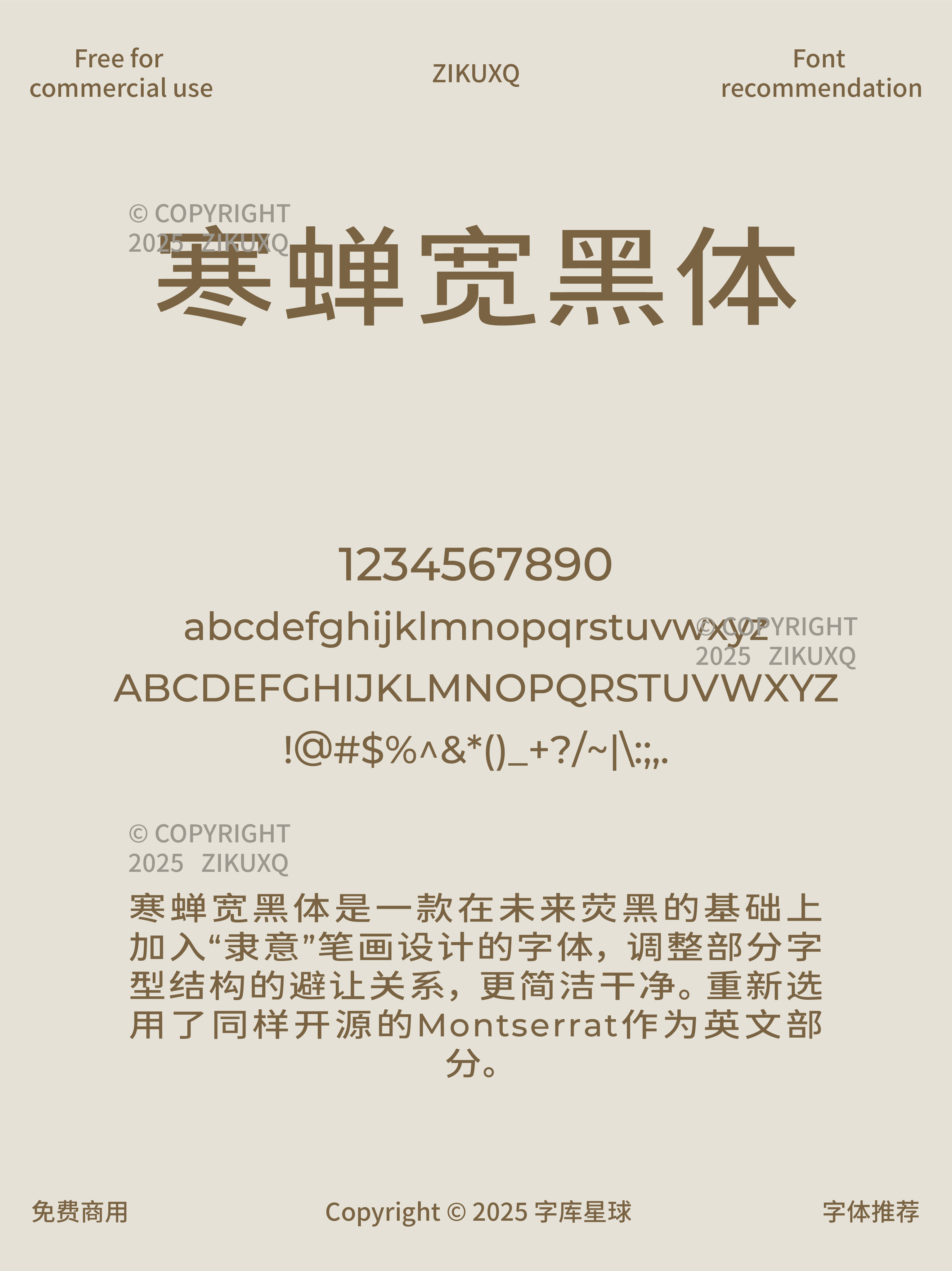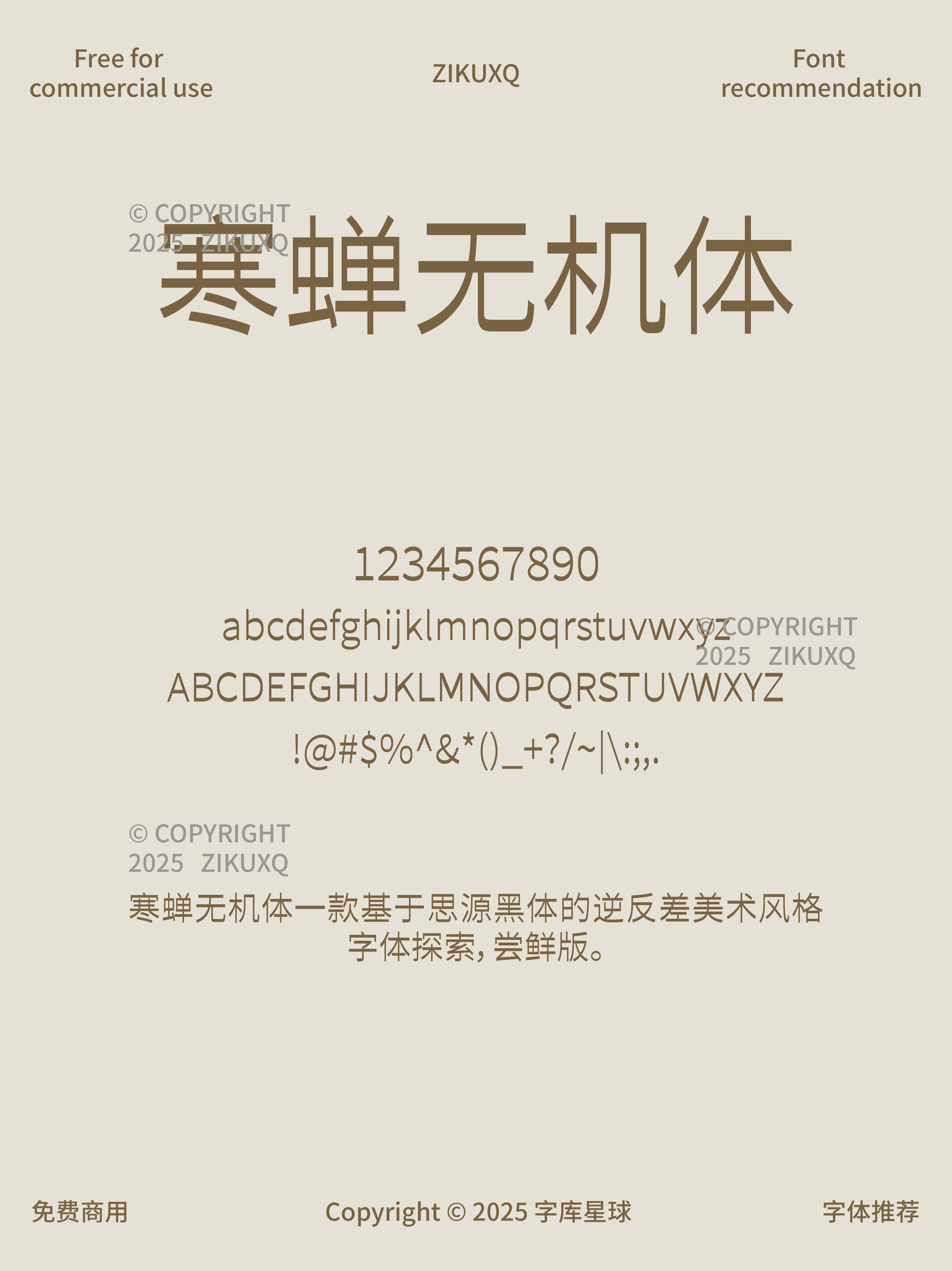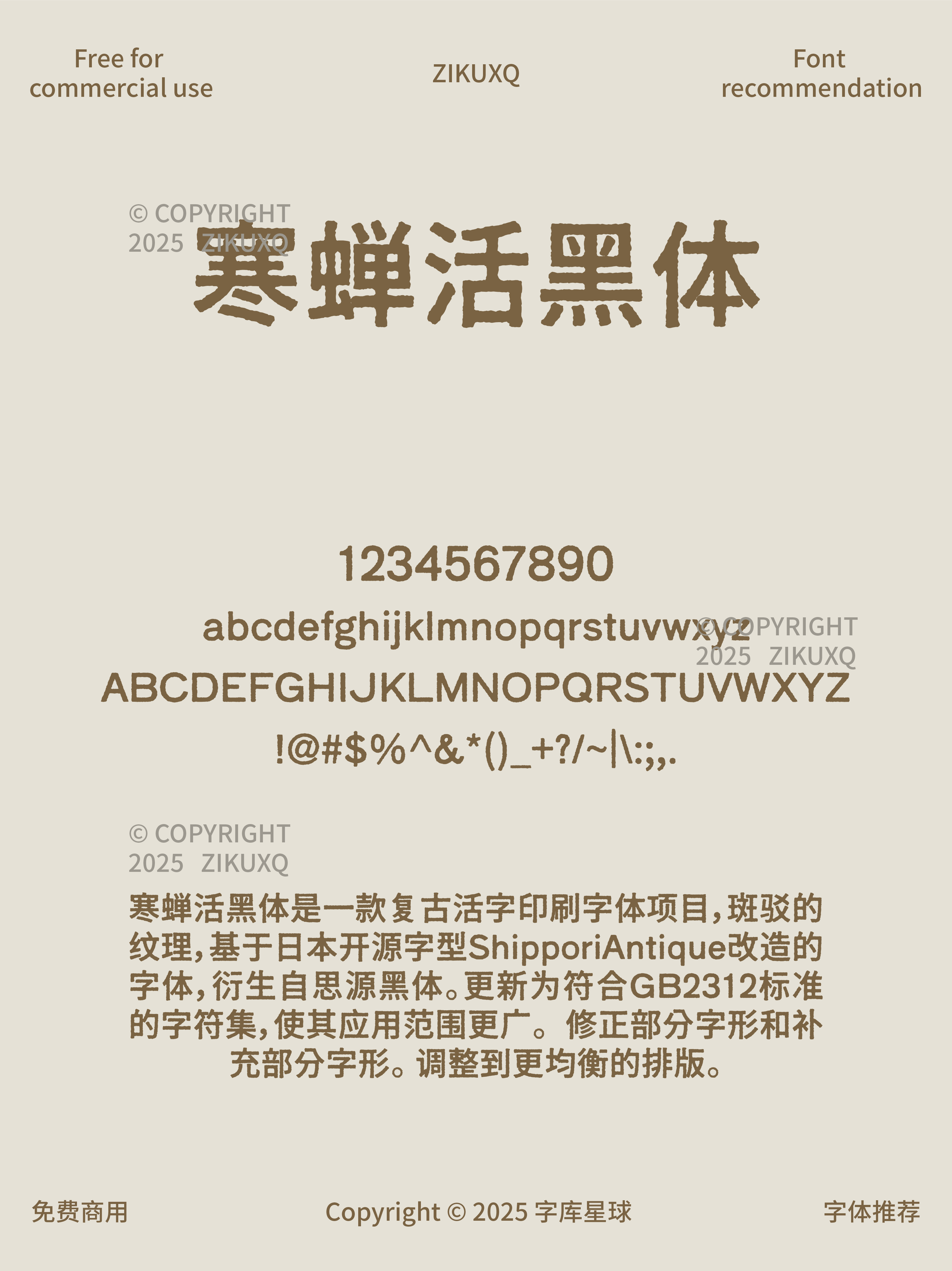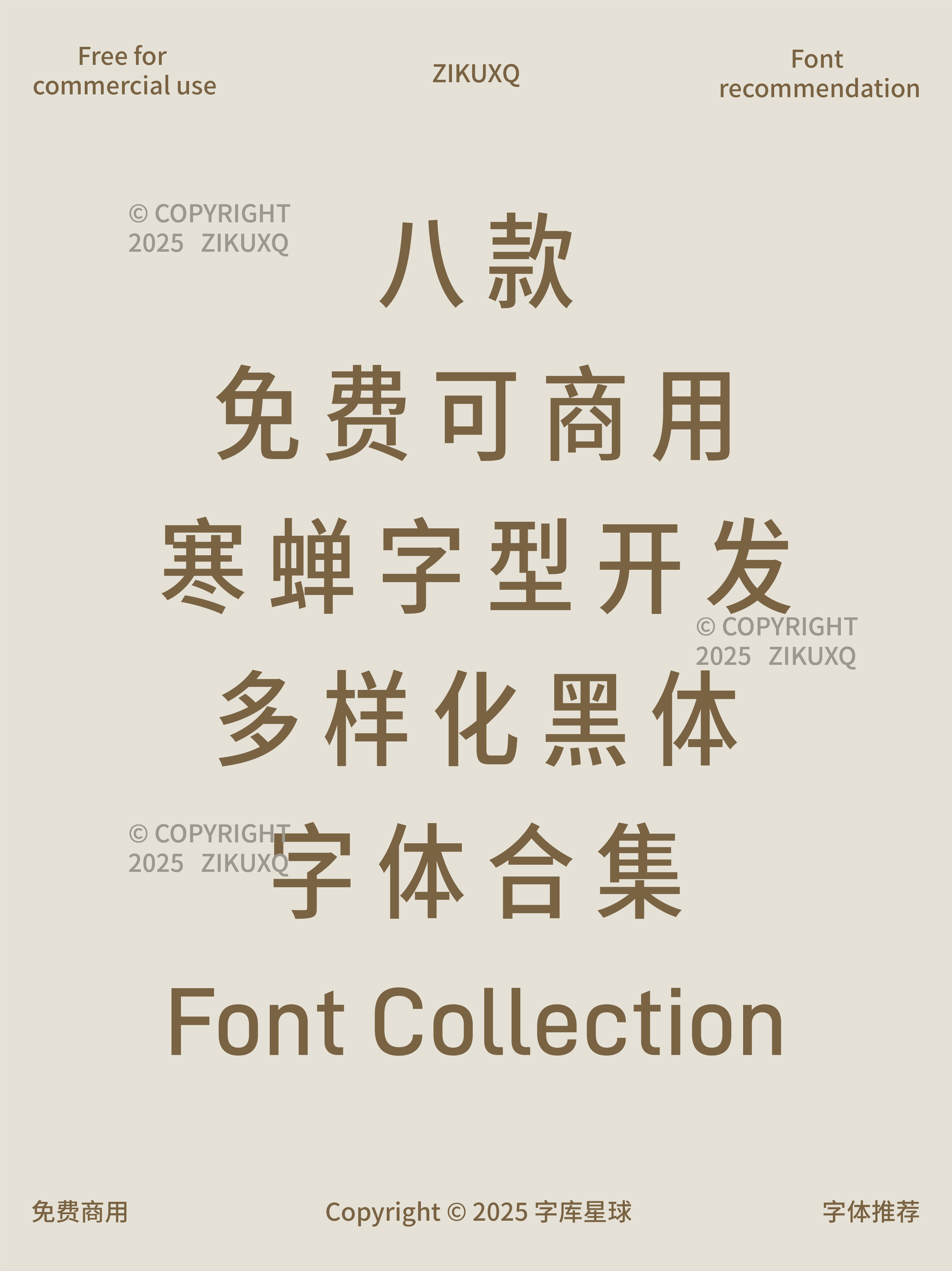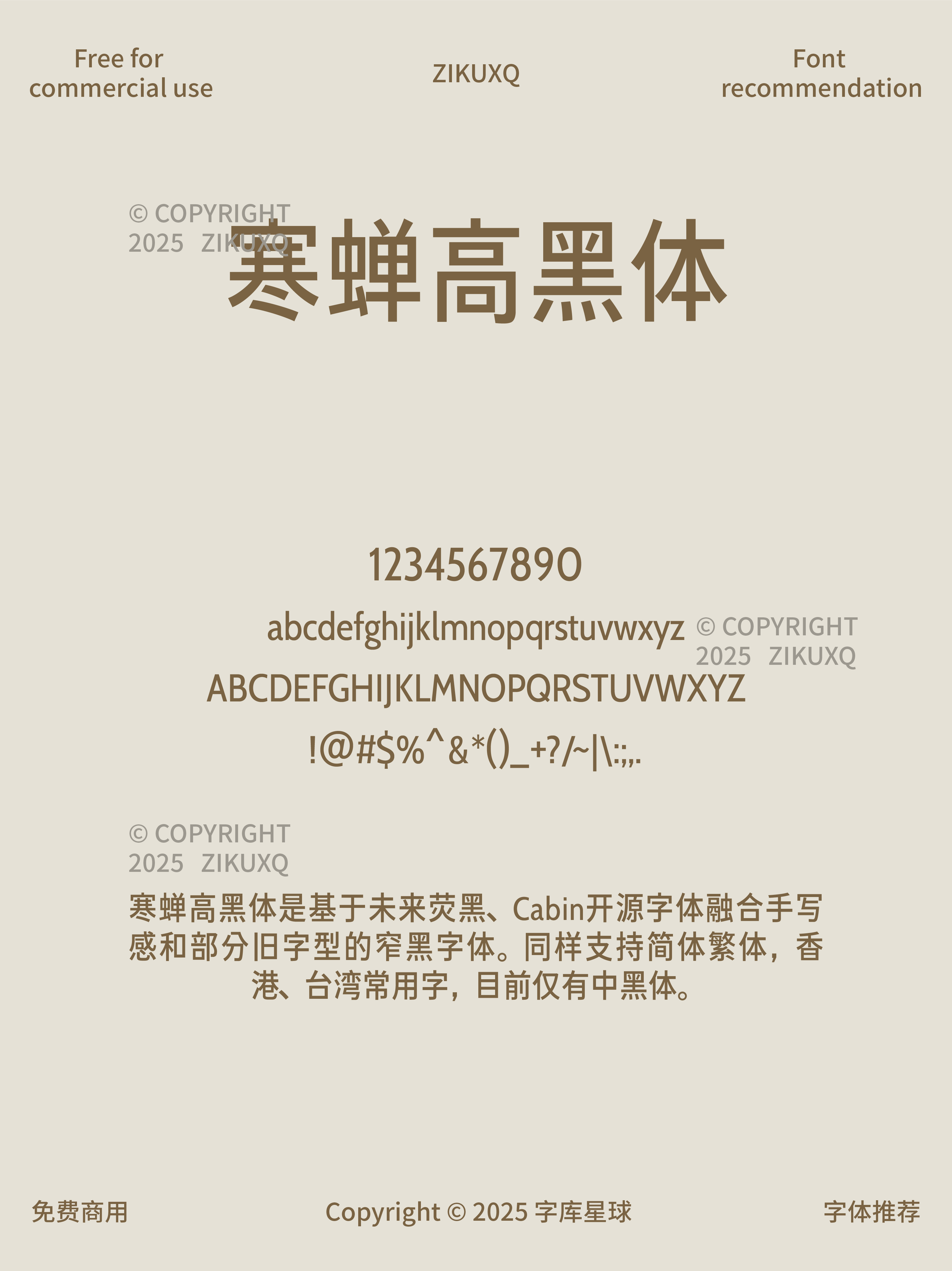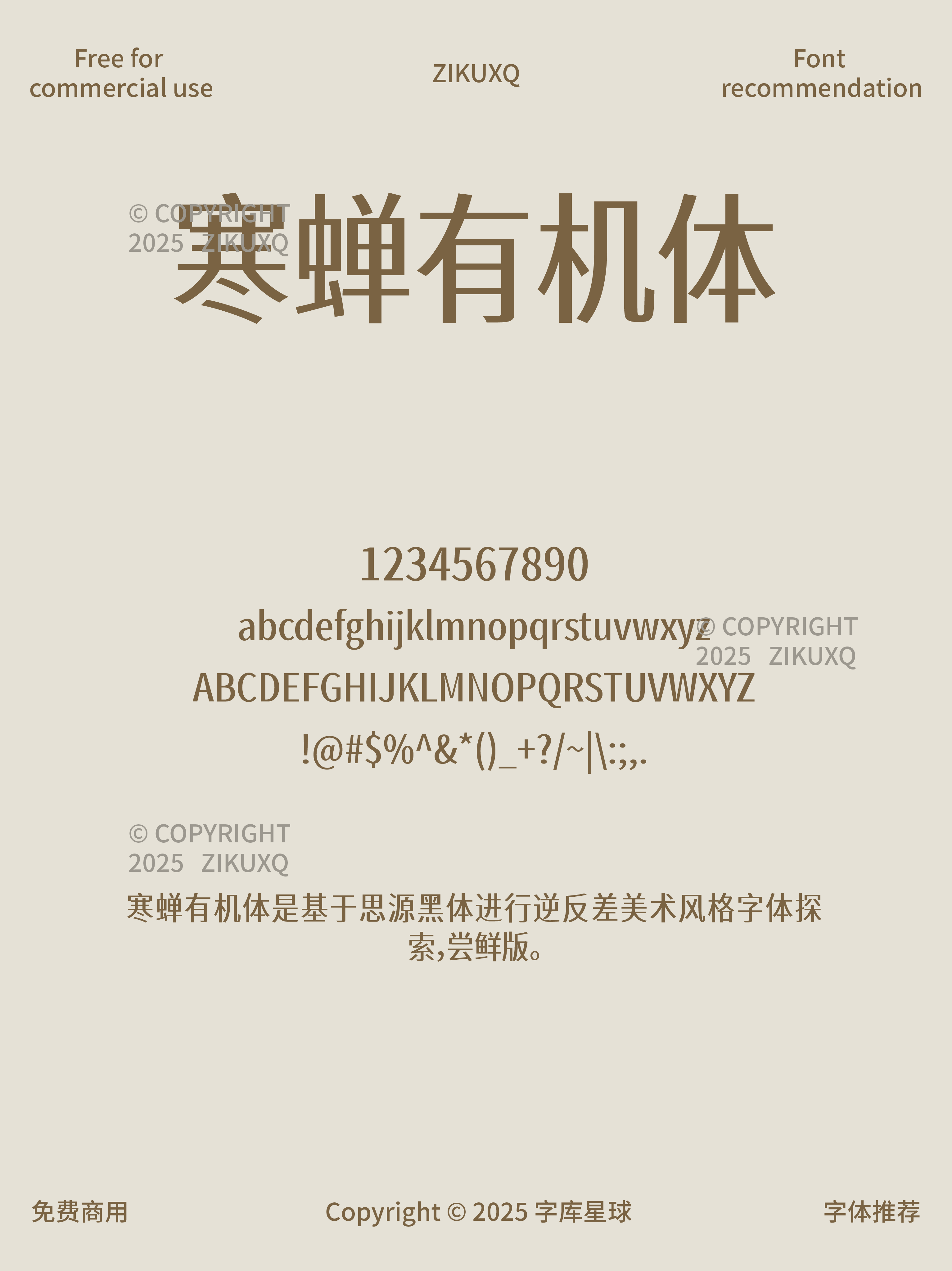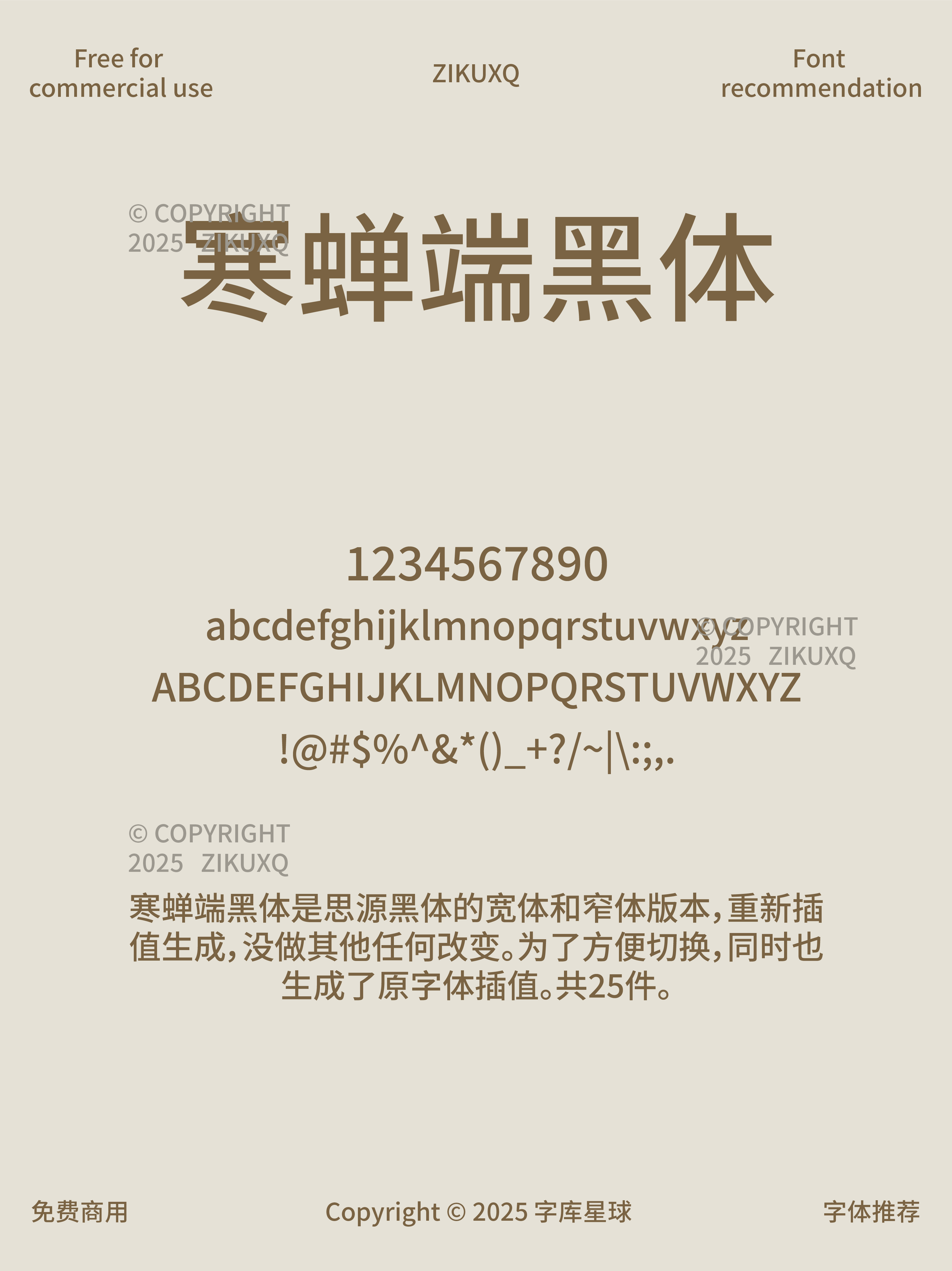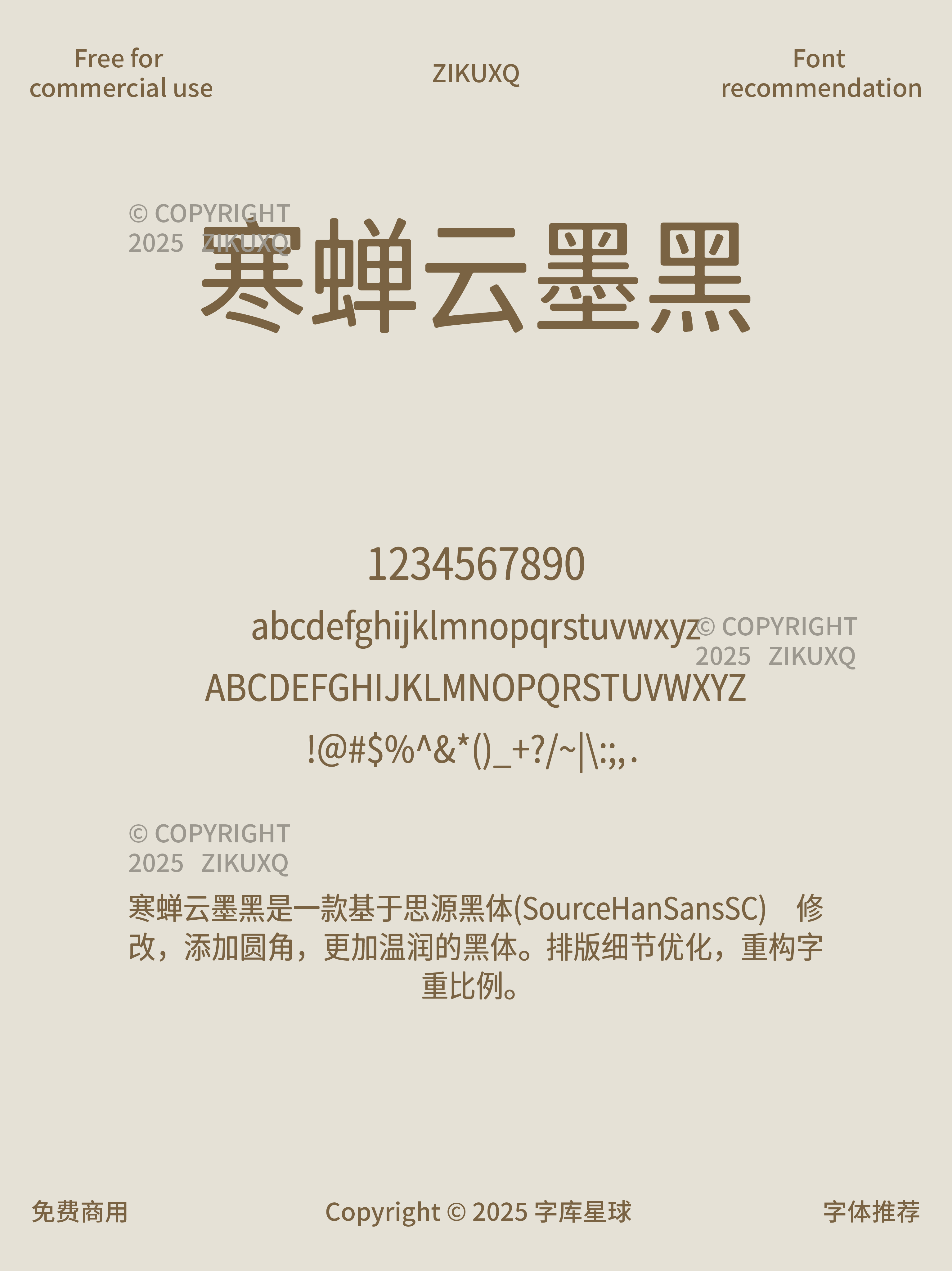
八款免费可商用寒蝉字型开发多样化黑体字体
今天给大家分享寒蝉字型的八款免费可商用黑体字体,轻松为你的设计增添亮点!
独特逆反差美术风格,探索不一样的视觉感受,设计尝鲜就选它!思源黑体宽体和窄体重新插值生成,简约大气,基础款永远经典,适配各种简约风设计。以思源黑体为基础,算法圆角化转换,保留原汁原味又更显圆润,给人亲切可爱之感。
这八款免费可商用的寒蝉黑体字体,每一款都独具特色,不管是海报设计、新媒体排版,还是包装设计,都能完美适配,为你的作品注入新活力,赶紧收藏用起来!